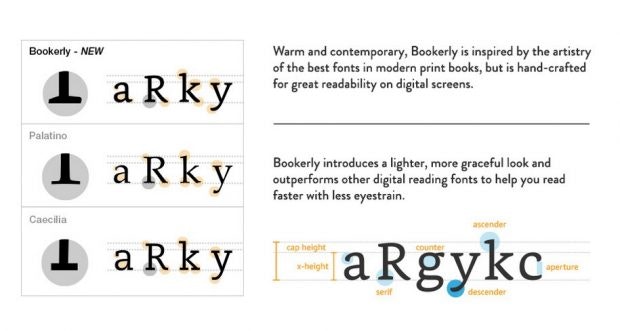
Amazon ändert die Schriftart im Shop – und das Netz rastet aus
Amazons neuer Font hat Serifen – und das bringt Nutzer zur Raserei. Dabei stellt sich die Frage: Ist eine serifenlose Schrift wirklich besser als eine mit Serifen? Es gibt eine überraschende Antwort.
Bei vielen Nutzern erscheinen seit kurzem die Texte auf der Amazon-Website oder in der App nicht mehr wie gewohnt in einer serifenlosen Schriftart, sondern in der Serifenschriftart „Amazon Bookerly“. Es ist nicht wirklich klar, ob Amazon hier einen seiner vielfältigen A/B-Tests durchführt und die Änderung nur punktuell erprobt wird oder ob es sich um eine langfristig geplante Änderung handelt, die jetzt sukzessive umgesetzt wird. Spannend ist vor allem die Frage, ob Amazon mit der Einführung der Serifen-Schriftart richtig liegt – oder einen Fehler begeht.
Amazon ändert überraschend die Schriftart
Die Änderung der Schriftart scheint einen Nerv zu treffen, allerdings einen schmerzhaften. Sonderlich gnädig nehmen die Nutzer die neue Serifen-Schriftart jedenfalls nicht auf, wie ein Blick auf das Stimmungsbarometer Twitter zeigt.
Der Tenor geht seitenweise so weiter, die Nutzer sind hochgradig irritiert und fordern mehr oder weniger vehement, dass Amazon zu seiner serifenlosen Schriftart zurückkehrt. Geradezu erheiternd ist Amazons Reaktion auf manchen Rant. Da heißt es in der Antwort eines Amazon-Mitarbeiters sinngemäß: „Sieht so aus, als hätten Sie Schwierigkeiten, sich an unsere neue Schriftart zu gewöhnen. Wir betrachten das mal als Feedback und geben es weiter.“
Die Suche nach dem Grund für diesen Aufschrei wegen Amazons Serifenschriftart führt zu einem scheinbar unumstößlichen Gesetz des Screendesigns. Schriften haben am Bildschirm gefälligst serifenlos zu sein. Dabei ist diese gefühlte Grundregel nicht in Stein gemeißelt und verliert langsam auch ihren Sinn.
Serifen oder serifenlose Schriftart am Bildschirm
Mit vs ohne Serifen. Hier die beiden Schriftarten Gill Sans und Georgia. (Grafik: t3n.de)
Mit und ohne Serifen. Hier die beiden Schriftarten Gill Sans und Georgia. (Grafik: t3n.de)
Serifen sind kleine Nasen am oberen und unteren Ende der Buchstaben. Ihre Aufgabe ist es, das Auge beim Lesen zu führen. Durch die Serifen entsteht für das Auge quasi der Eindruck einer Linie, was theoretisch das Lesen erleichtern soll.
Die Faustregel, dass Serifen generell nicht für die Bildschirmschriftarten tauglich sind, ging über lange Jahre hinweg hauptsächlich auf zwei Faktoren zurück:
• Die meisten Serifenschriftarten sind in einer Zeit vor dem Aufkommen der Bildschirme für den Druck gestaltet worden.
• Die Auflösung der Bildschirme war lange Zeit nicht gut genug, so kleine Details wie Serifen darzustellen. Dadurch wurde die eigentlich nutzerfreundliche Funktion der Serifen in das Gegenteil verwandelt: Nahe beieinanderliegende Buchstaben wie r und n verschmolzen durch undeutliche Serifendarstellung zu einem m.
Beide Faktoren deuten eher darauf hin, dass es grundlegende Gestaltungsfaktoren sind, die Schriftarten am Monitor  schlechter lesbar machen und nicht das Fehlen oder Vorhandensein von Serifen.
Heute gibt es serifentragende Schriftarten, die speziell für den Bildschirm entworfen wurden und eine gute Lesbarkeit bieten. Und die Auflösung und Pixeldichte der modernen Bildschirme kann mit vernünftig gestalteten Serifen längst umgehen. Theoretisch könnte jetzt das Urteil lauten: Es ist egal, setzt Serifen ein, wo ihr wollt, solange es Sinn ergibt. In Miniaturschriften also eher nicht. Leider ist der Nutzer aber nicht so einfach gestrickt, dass technisch gut lesbar auch beliebt bedeutet – wie Amazon mit seiner eigentlich ordentlich gestalteten Schriftart Bookerly gerade am eigenen Leib erleben muss.
Tatsächliche und gefühlte Lesbarkeit
Im Designtagebuch beschreibt Martin Liebig, Dozent für Mediengestaltung an der FH Gelsenkirchen, in seinem Artikel über „gefühlte Lesbarkeit“ ein interessantes Experiment zur Lesbarkeit von Schriftarten aus dem Jahr 2009. Rund 3.000 Menschen klickten sich durch Texte mit rund 110 Wörtern. Gemessen wurde die Lesezeit zwischen zwei definierten Messpunkten in über 1.440 typografische Konstellationen mit variierten Schriftgrößen, Zeilenabständen und Zeilenbreiten. Dieser Messung liegt die Annahme zugrunde, dass gute Typografie schneller lesbar ist. Zum Schluss wurden Sympathienoten für die Schriftarten abgefragt, die ein Bild über die gefühlte Lesbarkeit einer Schriftart ergeben.
Die tatsächliche Lesbarkeit
• Serifen oder serifenlose Schriftarten sind nicht generell schneller oder langsamer lesbar. Es scheint für die objektive Lesbarkeit egal zu sein, ob Serifen vorhanden sind oder nicht.
• Die beste Schriftart im Test war Arial, die schlechteste Corbel. Arial bot gerade einmal 3,9 Prozent mehr Geschwindigkeit. Für den Forscher keine eindeutige Aussage.
Die gefühlte Lesbarkeit
• Das Empfinden der Nutzer hat nichts mit der tatsächlichen Lesbarkeit einer Schriftart zu tun, es beruht auf subjektivem Empfinden.